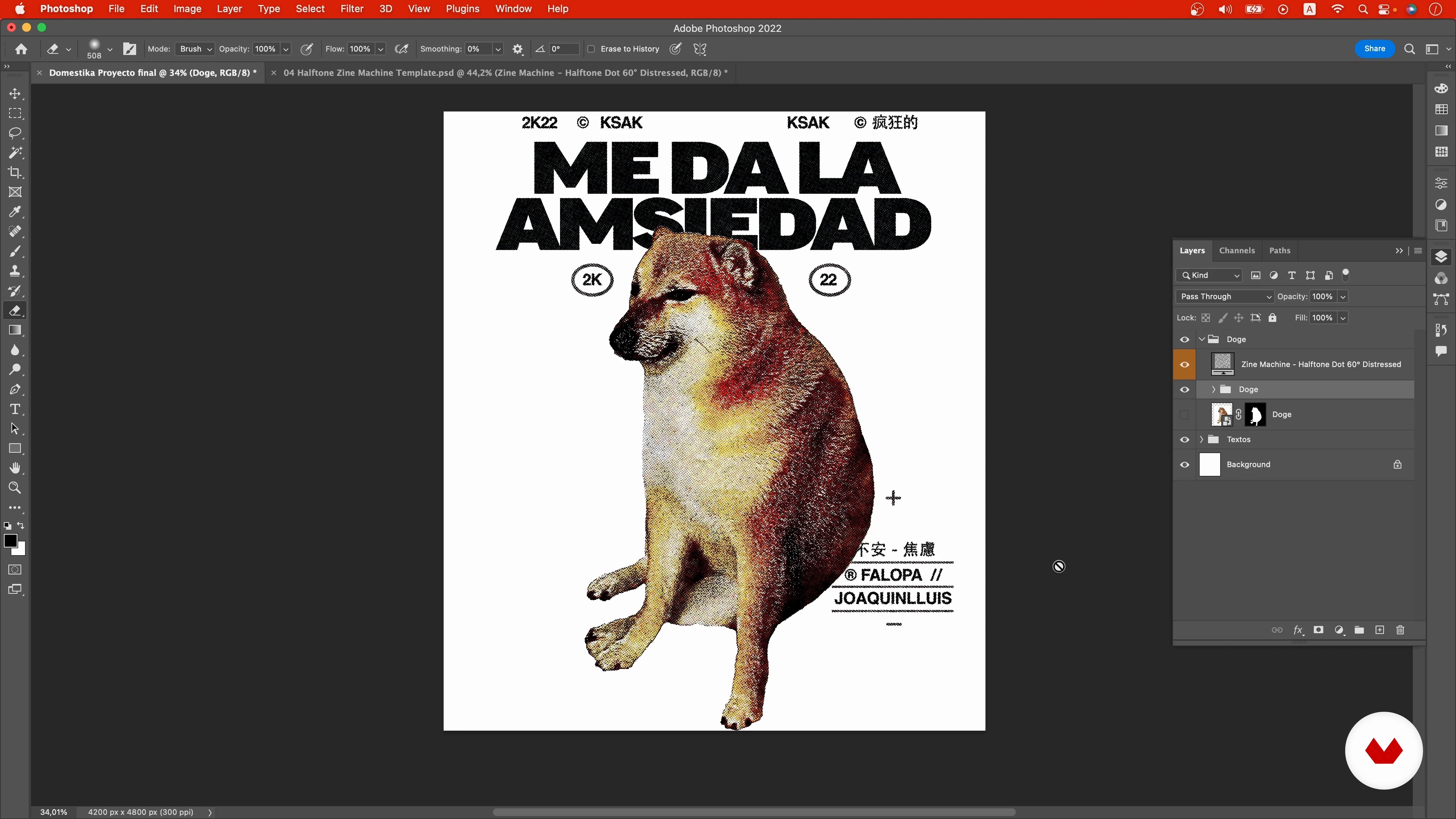
Création d'une typographie pour t-shirt
Traitement d'images 3
À propos de la leçon : Traitement d'images 3
“Enfin, je vais éditer l'image dans Photoshop pour obtenir le résultat que je recherche.”
Dans cette leçon, Joaquín Lluis aborde le sujet : Traitement d'images 3, qui fait partie du cours Domestika en ligne : Création d'une typographie pour t-shirt. Découvrez les secrets de la création de t-shirts et exprimez vos idées créatives..
“Revenons à Photoshop. ouvrons le fichier associé à ce filtre. je vais vous expliquer en détail son fonctionnement et vous montrer quelques exemples. Très bien. ici nous avons une image de fond et vous voyez ici comment le filtre de trame Halftone est appliqué à 60 degrés. qui présente un aspect érodé. on pourrait dire qu'il s'agit d'une forme d'usure si l'on examine de près ; voici l'image initiale et voici le rendu après application du filtre ou de la couche ajoutant cette Mais comme mentionné précédemment. nous avons de nombreuses variantes. Nous avons celle-ci qui a un angle. et celle-ci...”